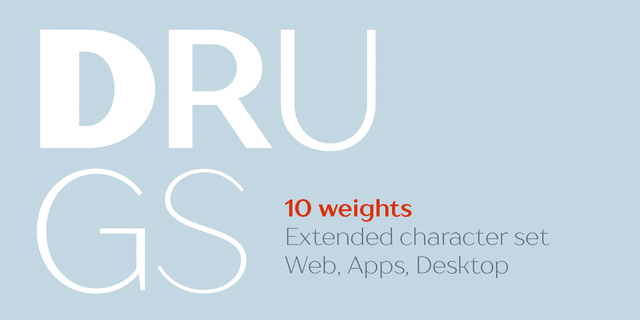
Шрифт Drugs разработан специально для фармацевтики и бытовой химии. Он идеально подойдет для дизайна упаковки лекарства, зубной пасты или стирального порошка. Гарнитура имеет 5 насыщенностей, наклонные начертания и приспособлена для любой поверхности: бумага, картон, металл, стекло. Drugs одинаково хорошо выглядит как в текстовом, так и в акцидентном применении. Шрифт разработан в студии TypeType в 2014 году.
Ассоциации c семейством TT DrugsКачества и характер:
деликатный, чистый, легкий, худой, прохладный, свежий, тонкий, современный, лаконичный, ясный, ровный, понятный, качественный, невесомый, прозрачный, городской, точный, минималистичный, четкий, интимный, хрупкий, логичный, воздушный, стеклянный, острый, простой, деловой, нейтральный, статичный, строгий, твердый, доступный, элементарный, правильный, серьезный, устойчивый, стабильный, самостоятельный, ответственный, западный, спокойный, оптимальный, убедительный, холодный, надежный, важный, солидный, сильный, мотивирующий, авторитетный